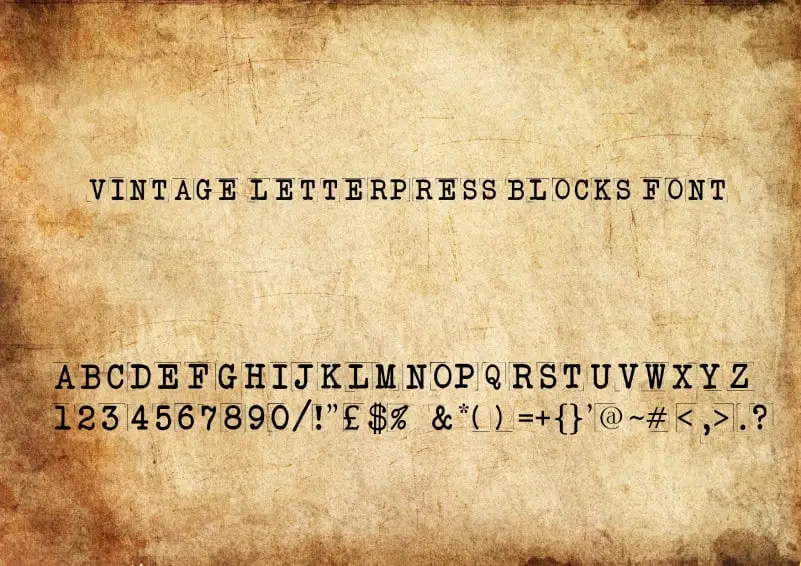
Vintage Letterpress Blocks Font – Download Grátis
A Vintage Letterpress Blocks Font é uma jóia do design tipográfico, embalada num elegante estilo vintage ou antigo. Inspirada em blocos de letras impressas com pressão letterpress, esta fonte traz a sensação de qualidade que as antigas impressões forneciam. Ela apresenta um alfabético completo de formas sóbrias e refinadas, criando uma atmosfera nostálgica e sofisticada. Estes designs de letras são provavelmente de antes do ano de 1960, com possibilidade ainda mais antigos, talvez datados da década de 1900. A fonte transmite uma sensação de história, realçando o valor intrínseco e a elegância que as antigas impressões proporcionavam. Ideal para quem busca um estilo tipográfico único e com profundidade histórica, esta Vintage Letterpress Blocks Font é perfeita tanto para trabalhos profissionais como para criações artísticas, oferecendo uma paleta de opções para personalizar qualquer projeto. Seja para contratos legítimos ou letras de amor, este design clássico traz um toque único e memorável a cada texto impresso.